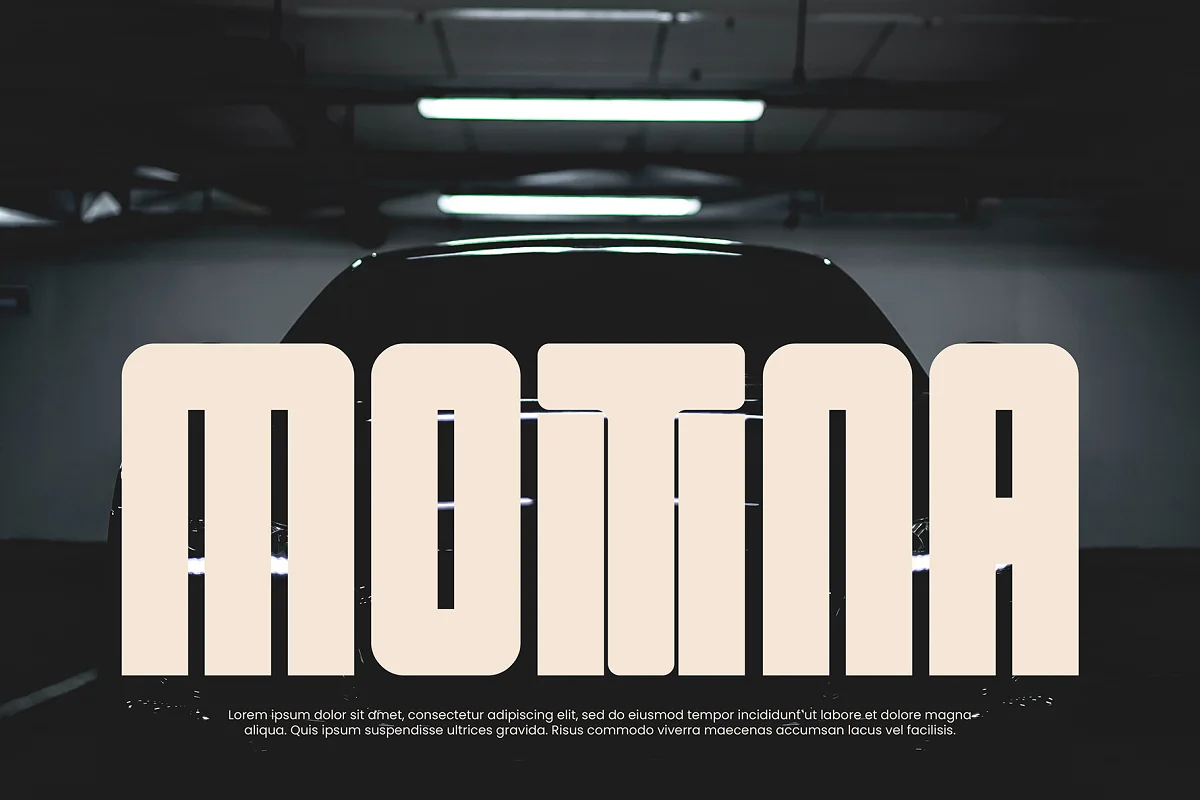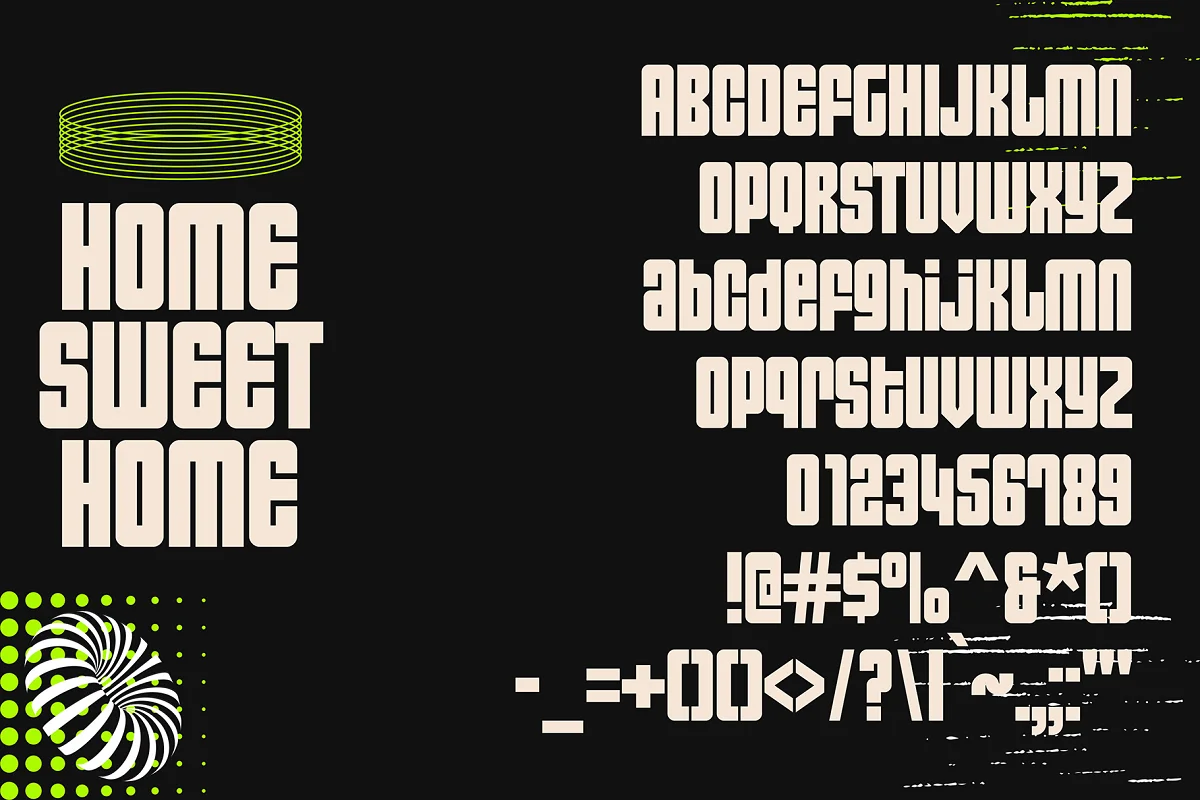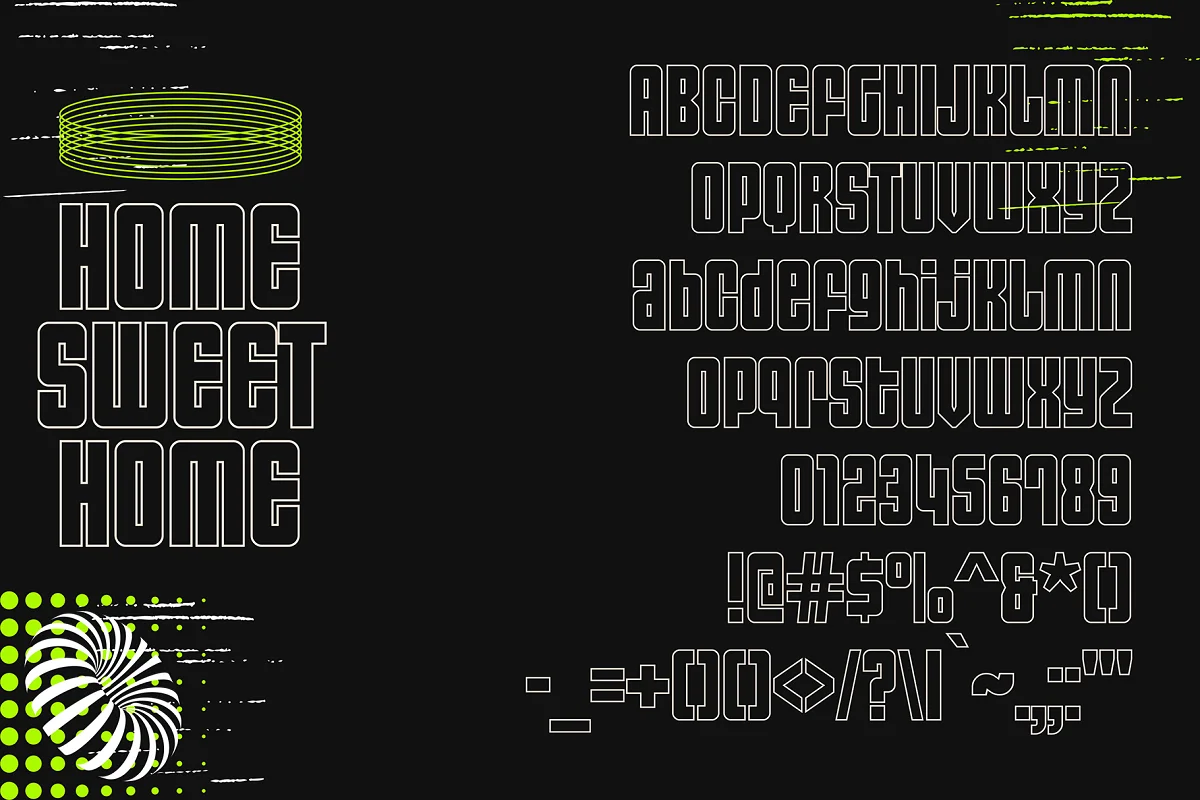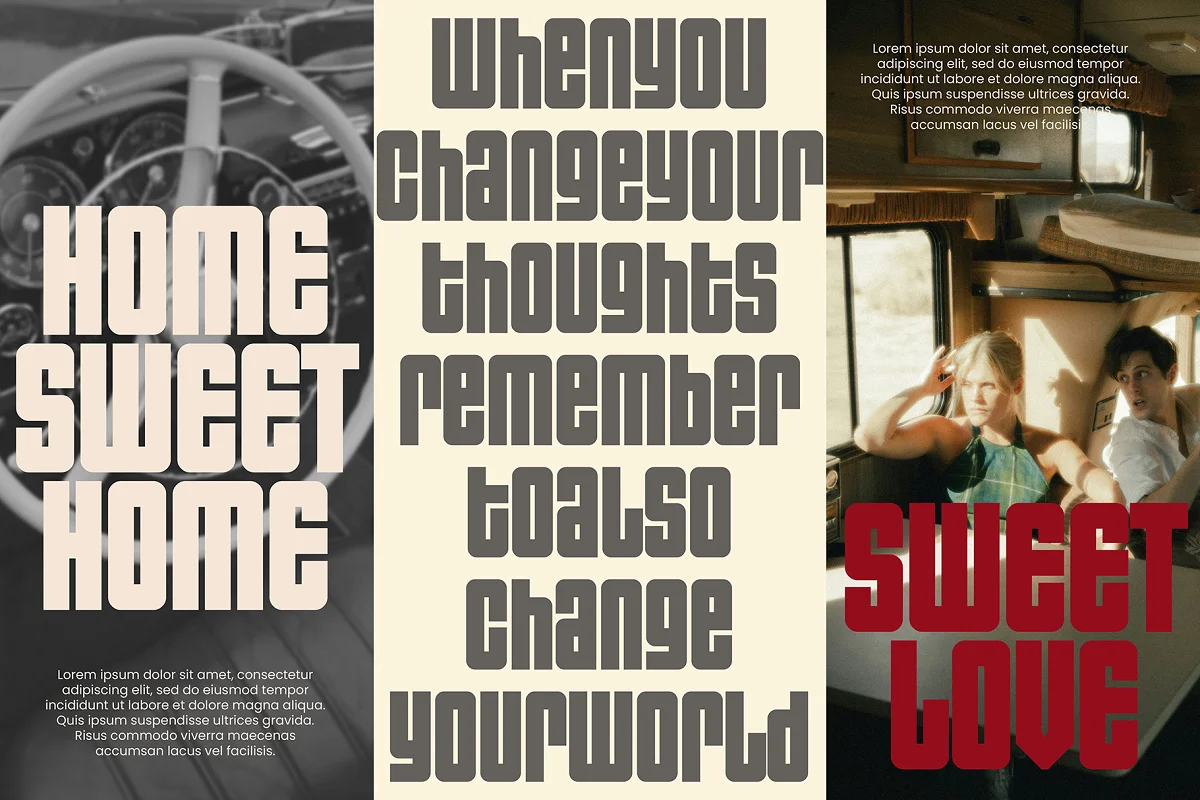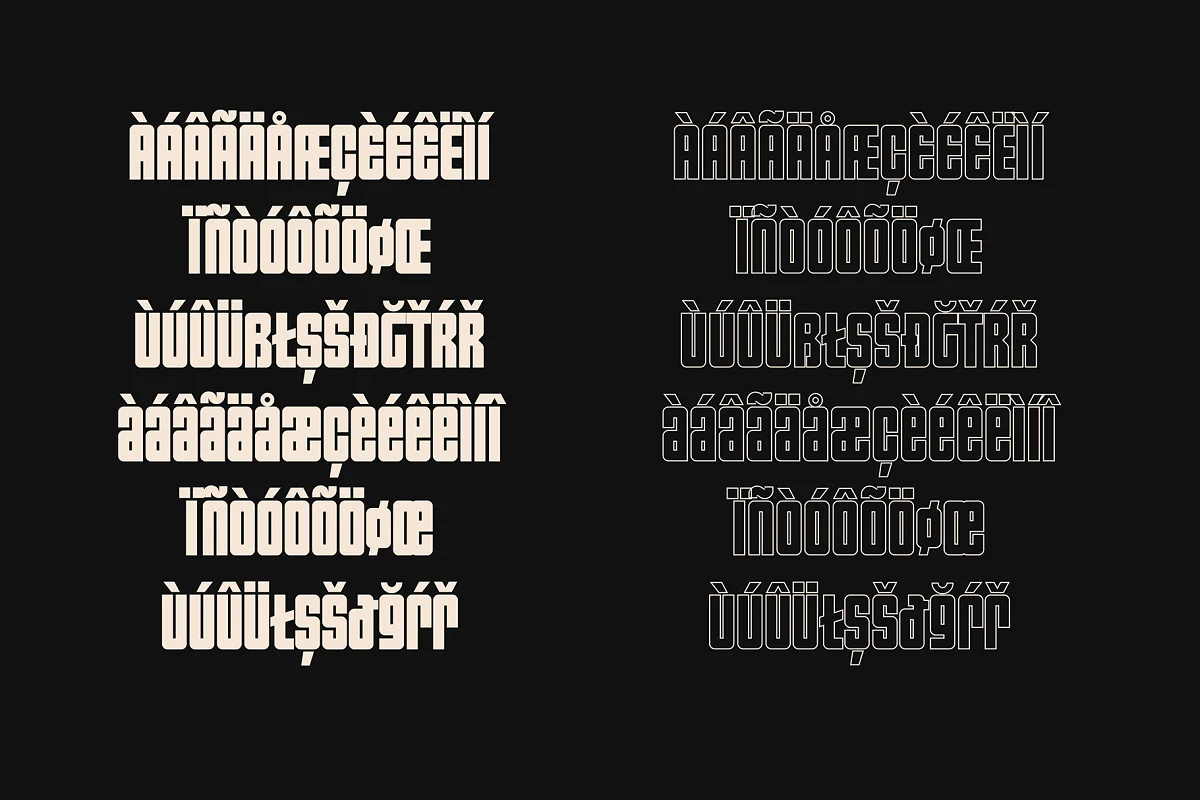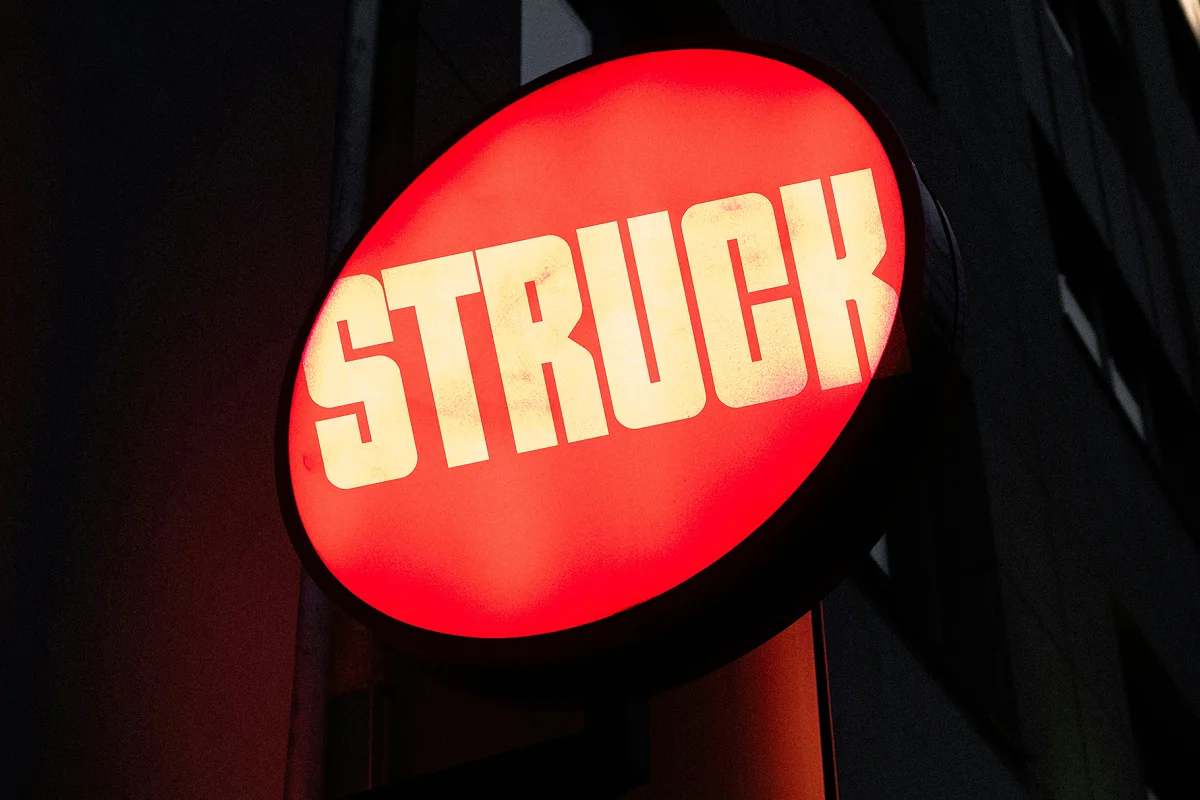
Giới thiệu Staccto , một phông chữ hiển thị đơn giản và mang tính trang trí. Rất hoàn hảo cho bạn, những người cần một kiểu chữ cho thiết kế logo, tạp chí, mạng xã hội, tài liệu quảng cáo, v.v.
- Chữ hoa
- Chữ thường
- Chấm câu
- Chữ số
- Hỗ trợ đa ngôn ngữ